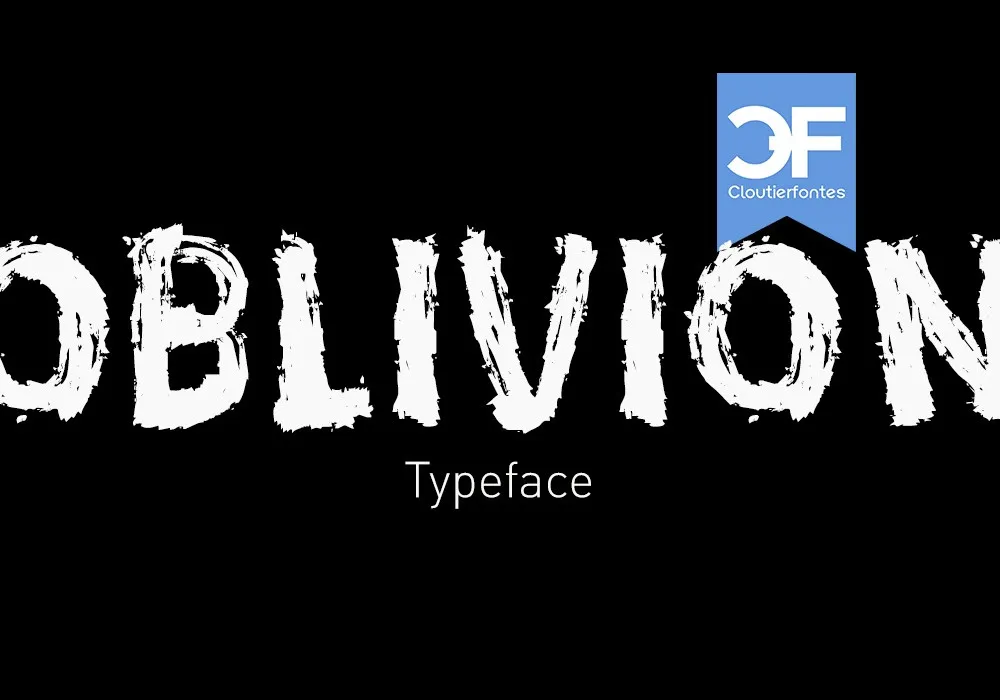
CF Oblivion font – Download Grátis
A CF Oblivion é uma fonte curvada feita à mão, perfeita para aqueles que buscam algo que dê vida a suas criações digitais. Criada pelo designer CloutierFontes, essa fonte ideal para logos e títulos de filmes ou livros, bem como textos longos e secundários, fazendo o seu trabalho um verdadeiro show de platéia. Esse all caps handwritten display font não apenas adiciona uma camada de originalidade a qualquer projeto, mas também permite que você personalize sua marca ou mensagem de maneira única. Conecte-se à CF Oblivion em redes sociais, eletrodomésticos dos seus títulos cinematográficos ou mesmo nas páginas internas de seus livros. Com sua versatilidade para ser usada com linhas gerais (sans) ou serifadas, a CF Oblivion é uma escolha inteligente para qualquer projeto visual que deseje chamar atenção e se destacar. Seja em longos textos ou textos secundários curtos, essa fonte irá transformar seu trabalho de forma impactante.
Designer: CloutierFontes